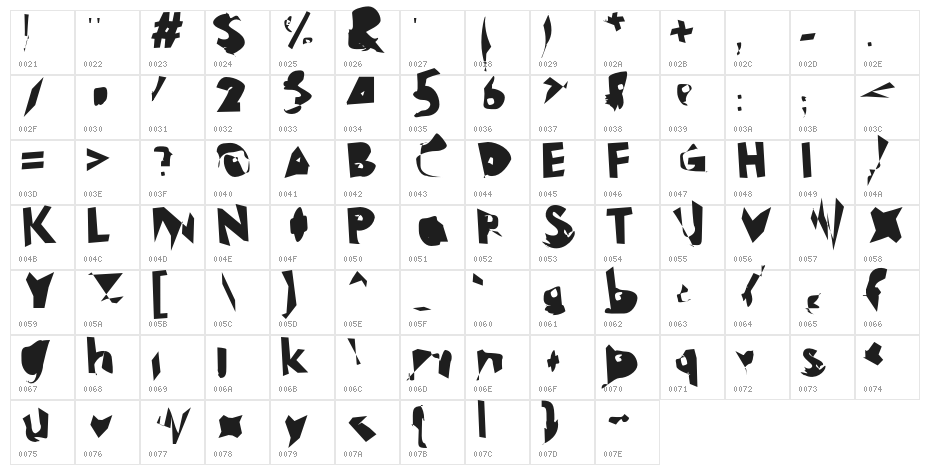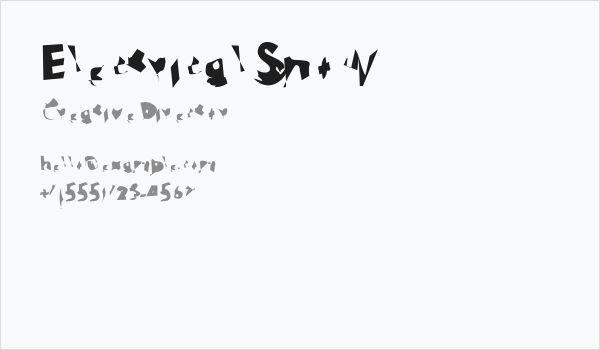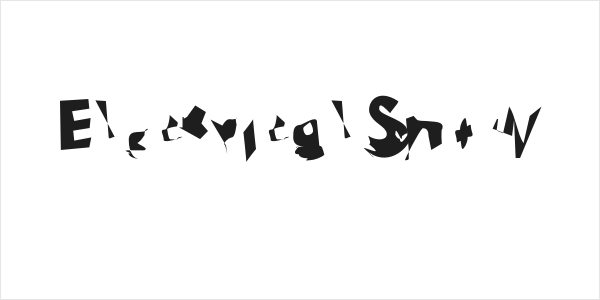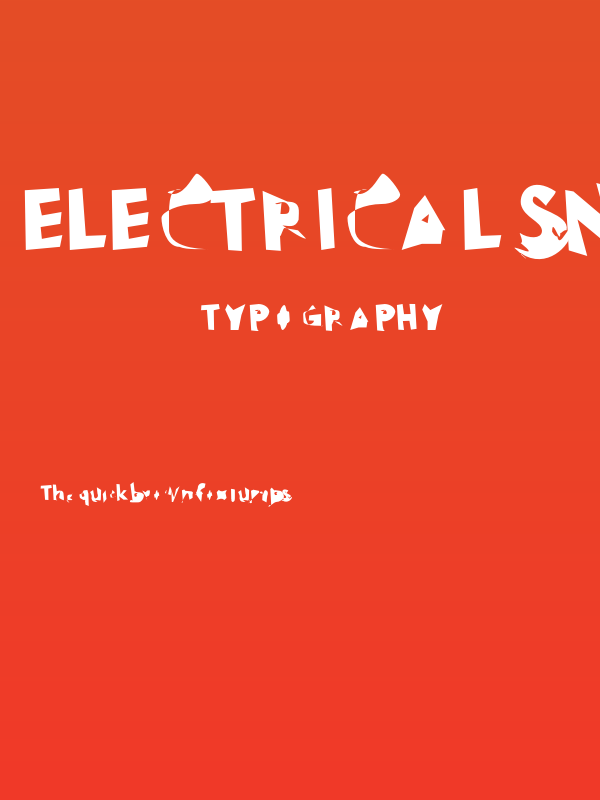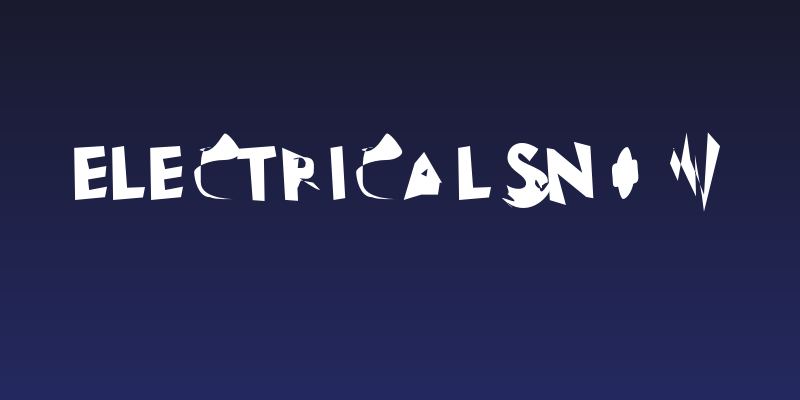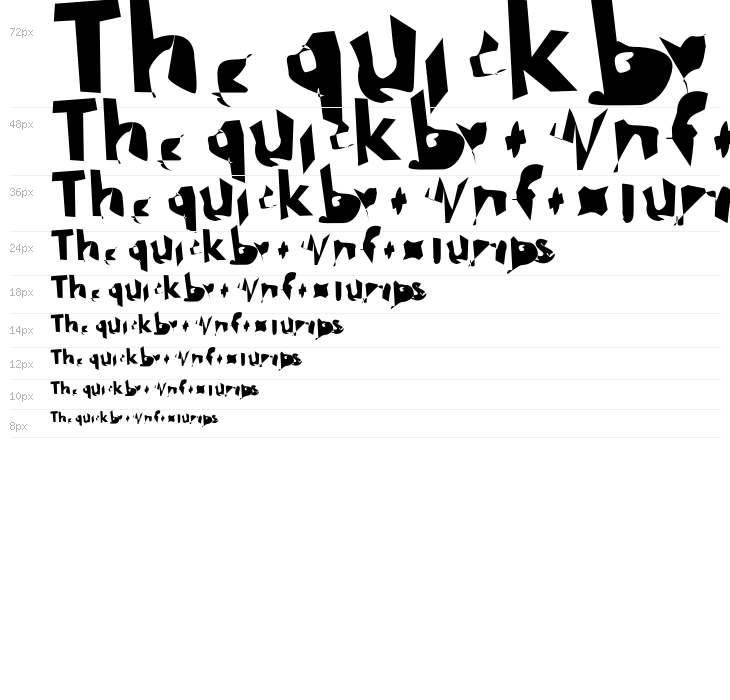
Electrical Snow Font
✎ Distorted Eroded
| Estilo geral | Modern, Abstract |
| Caso de uso | Logos, Headlines, Artistic projects |
| Projetos propostos | Ideal for album covers, poster designs, or any creative project needing a striking, unconventional typeface. |